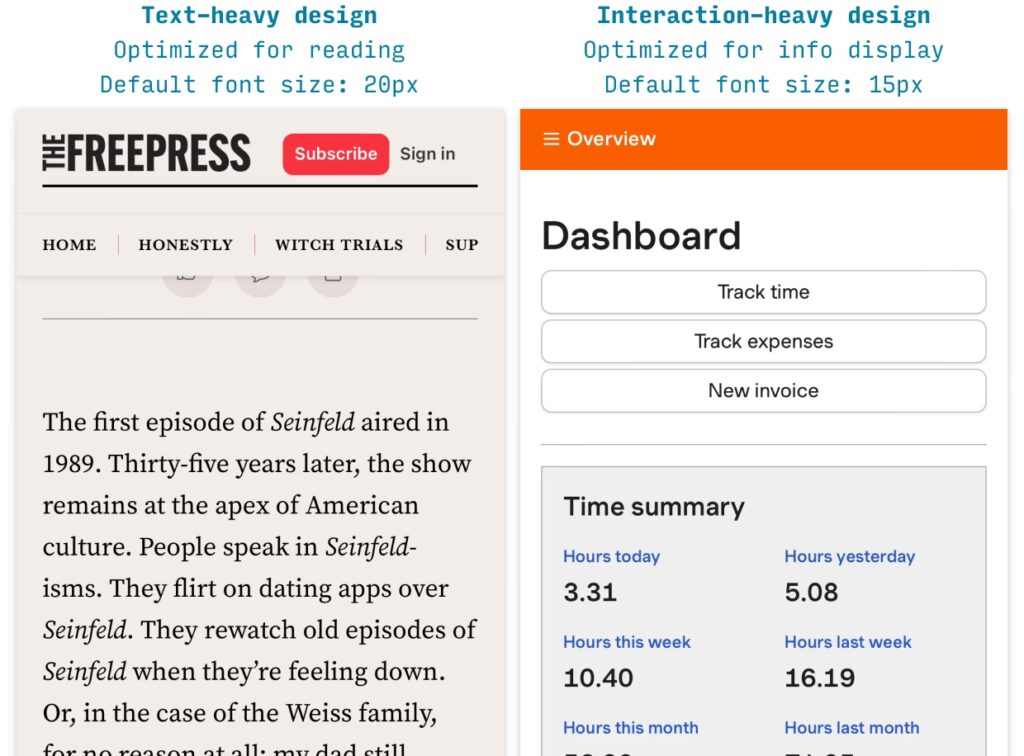
I en verden hvor mobiltelefonen er vores primære adgang til internettet, er det afgørende, at indhold er letlæseligt og behageligt at interagere med. En af de største udfordringer for webdesignere og indholdsskabere er at vælge den rette skriftstørrelse, der sikrer optimal læsbarhed på små skærme uden at kræve konstant zoomning. Dårlig typografi kan hurtigt frustrere brugere og få dem til at forlade din side. Denne omfattende guide vil dykke ned i de bedste praksisser og anbefalinger for at vælge den ideelle skriftstørrelse til mobile skærme, så du kan skabe en gnidningsfri og tilgængelig brugeroplevelse for alle.
Grundlæggende Principper for Mobil Typografi
Mobil typografi handler om struktur, afstand og klarhed for at gøre indholdet let at læse, uanset skærmstørrelsen. Ved at fokusere på nøgleprincipper kan du skabe en brugervenlig oplevelse for alle.
Anbefalede Skriftstørrelser
En af de mest fundamentale anbefalinger er at starte med en grundlæggende skriftstørrelse på 16 pixel for brødtekst. Denne størrelse er bredt anerkendt som den mest komfortable for de fleste læsere og eliminerer behovet for at zoome ind for at læse indholdet. Ud over brødteksten er det essentielt at etablere et klart visuelt hierarki for at guide brugeren gennem indholdet og fremhæve de vigtigste elementer. Dette opnås ved at tildele forskellige skriftstørrelser til forskellige elementer som titler, sekundær tekst og inputfelter.
Anbefalede Skriftstørrelser til Mobilskærme
| Tekstelement | Anbefalet Størrelse (px) |
|---|---|
| Sidetitler / Overskrifter | 28-40px |
| Brødtekst | 16-20px |
| Sekundær Tekst (f.eks. billedtekster, noter) | 14-18px |
| Inputfelter | Mindst 16px |
| Listeemner | 16px (standard) / 14px (tættere lister) |
Linjehøjde og Kontrast
Ud over selve skriftstørrelsen spiller linjehøjden en kritisk rolle for læsbarheden. En god tommelfingerregel er at sætte linjehøjden til 1.5 gange skriftstørrelsen. Dette skaber tilstrækkelig plads mellem tekstlinjerne, hvilket reducerer øjenbelastning og gør det lettere at scanne teksten hurtigt. For eksempel, hvis din brødtekst er 16px, bør linjehøjden være omkring 24px (16 * 1.5). En anden afgørende faktor er kontrasten mellem tekst og baggrund. Ifølge WCAG (Web Content Accessibility Guidelines) anbefales et kontrastforhold på mindst 4.5:1 for normal tekst og 3:1 for stor tekst. Høj kontrast, som sort tekst på en hvid baggrund, er altid et sikkert valg og sikrer maksimal læsbarhed for alle brugere, herunder dem med synsnedsættelser.
Skalerbare Skrifttyper og Fleksibelt Design
For at sikre, at din typografi tilpasser sig problemfrit på tværs af forskellige enhedsstørrelser – fra de mindste smartphones til tablets og desktops – er det essentielt at anvende skalerbare skriftstørrelser. Dette betyder, at man bevæger sig væk fra faste pixelværdier og i stedet benytter sig af relative enheder. Relative enheder tillader teksten at skalere automatisk baseret på skærmstørrelsen, hvilket skaber en mere robust og fremtidssikret typografisk løsning.
Relative Enheder: Em og Rem
De mest almindelige relative enheder er em og rem. En 'em' enhed er relativ til dens forældreelements skriftstørrelse, mens en 'rem' (root em) enhed er relativ til rodfontstørrelsen (typisk defineret på <html> elementet). Dette gør 'rem' særligt nyttig, da en ændring af rodfontstørrelsen automatisk skalerer alle 'rem'-baserede elementer proportionelt. For eksempel, hvis din basefontstørrelse er sat til 16px på <body> eller <html> elementet, vil 1em eller 1rem svare til 16px. En overskrift på 2rem vil så være 32px (2 * 16px). At bruge disse enheder gør det nemt at implementere en responsiv typografi, der justerer sig dynamisk. Ved at sætte breakpoints kan du finjustere skriftstørrelserne for specifikke skærmbredder, hvilket giver dig fuld kontrol over brugeroplevelsen på tværs af enheder.
Test på Rigtige Enheder
Uanset hvor omhyggelig din planlægning og kodning er, er den ultimative test altid at se dine designs på rigtige enheder. En skriftstørrelse, der ser perfekt ud på din store designskærm, kan opføre sig uventet på en lille mobilskærm. Brug værktøjer, der giver dig mulighed for at se dine designs direkte på en mobiltelefon eller tablet. Det er også afgørende at teste, hvordan din tekst skalerer ved at zoome ind til op til 200%. Dette sikrer, at teksten forbliver læselig og at layoutet ikke bryder sammen, hvilket er et vigtigt aspekt af tilgængelighed for brugere med synshandicap.
Detaljerede Retningslinjer for Forskellige Elementer
For at opnå et klart og effektivt design er det vigtigt at forstå, hvordan forskellige tekstelementer skal behandles typografisk på mobile skærme.
Titler og Hovedtekst
Titler er dine brugeres første møde med indholdet, og de skal være iøjnefaldende. Størrelser mellem 28-40px er ideelle til sidetitler, da de skaber et stærkt visuelt anker og guider brugeren. Brødtekst, som udgør størstedelen af dit indhold, bør som nævnt holdes mellem 16-20px for optimal læsekomfort. Det handler om at finde en balance, hvor teksten hverken er for lille til at anstrenge øjnene eller for stor til at virke klodset.
Sekundær Tekst og Inputfelter
Sekundær tekst, såsom billedtekster, undertekster eller mindre vigtige detaljer, kan være lidt mindre end brødteksten, typisk 14-18px. Det er vigtigt, at der stadig er en tydelig forskel i størrelse, så det ikke forveksles med den primære tekst. En generel anbefaling er at gøre sekundær tekst omkring 2 størrelser mindre end din brødtekst for at sikre en klar visuel adskillelse. For inputfelter er det en streng regel: skriftstørrelsen skal være mindst 16px. Hvis den er mindre, vil iOS-browsere automatisk zoome ind på feltet, hvilket ofte skjuler dele af formularen og tvinger brugeren til manuelt at zoome ud, hvilket er en dårlig brugeroplevelse.
Lister og Specifikke OS-standarder
Lister er et almindeligt element på mobile sider. Standardlisteelementer er ofte 16px, men tættere lister, som dem i sidepaneler, kan være 14px, eventuelt med en federe vægt for at kompensere. Det er også værd at bemærke, at forskellige operativsystemer (OS) har deres egne typografiske retningslinjer, som det kan være nyttigt at kende til, især hvis du designer apps. Androids Material Design anbefaler for eksempel 16sp (scalable pixels) for standard brødtekst og listeelementer, og 20sp for titler. iOS's retningslinjer for SF Pro-skrifttypen angiver 17px som standard for brødtekst og 15px for sekundær tekst. Selvom disse er specifikke for apps, giver de en god indikation af, hvad brugerne forventer af læsbarhed på mobile enheder.
Optimering for Læsevenlighed og Tilgængelighed
God typografi går hånd i hånd med tilgængelighed. Her er yderligere tips til at forbedre læsevenligheden for alle brugere.
Tegn pr. Linje og Skrifttypevalg
For at optimere læsevenligheden yderligere, bør du sigte efter 30-40 tegn pr. linje på mobile skærme. Dette minimerer øjenbevægelser og gør teksten lettere at følge. Når det kommer til valg af skrifttype, er sans-serif skrifttyper som Arial, Open Sans eller Roboto generelt at foretrække på digitale skærme, især små mobilskærme. Deres rene linjer og fravær af dekorative udsmykninger (serif'er) gør dem mere læselige ved mindre størrelser. Selvom seriffonter kan bruges, bør de testes grundigt for læsbarhed på mobil, især i mørk tilstand.
WCAG Retningslinjer for Kontrast
At overholde WCAG's retningslinjer for kontrast er ikke kun et spørgsmål om design, men også om tilgængelighed. En høj kontrast sikrer, at dit indhold er læseligt for alle, uanset synsevne. Et klassisk eksempel er sort tekst (#000000) på en hvid baggrund (#FFFFFF), som giver et fremragende kontrastforhold.
Anbefalede Kontrastforhold (WCAG)
| Element | Anbefalet Kontrastforhold |
|---|---|
| Normal Tekst | 4.5:1 minimum |
| Stor Tekst (24px+ eller 18px+ fed) | 3:1 minimum |
| Interaktive Elementer (f.eks. ikoner, knapper) | 3:1 minimum |
Det er vigtigt at sikre, at selv interaktive elementer har tilstrækkelig kontrast, så de er tydelige og brugbare for alle.
Fremtidens Typografi: Intrinsic Type
Mens vi i dag fokuserer på responsiv typografi med relative enheder og breakpoints, kigger fremtiden mod 'intrinsic typography'. Dette er et koncept, hvor tekstens stil defineres ud fra dens proportion til det område, den befinder sig i, snarere end viewporten. Målet er at øge fleksibiliteten og forenkle koden. Resultatet er, at tekst 'selvjusterer' sig til sin container, hvilket potentielt kan give en næsten ubegrænset variation af skriftstørrelser, der passer perfekt til ethvert rum. Selvom dette stadig er et område under udvikling, understreger det vigtigheden af at tænke fremadrettet og designe med fleksibilitet for øje.
Konklusion
At vælge den rette skriftstørrelse til mobile skærme er en grundsten i godt webdesign og en afgørende faktor for brugeroplevelsen. Ved at følge de grundlæggende principper – en solid basefontstørrelse på 16px for brødtekst, anvendelse af relative enheder som em eller rem, etablering af et klart visuelt hierarki, sikring af høj kontrast og regelmæssig test på rigtige enheder – kan du skabe en hjemmeside, der ikke kun ser flot ud, men også er yderst læsbar og tilgængelig for alle. Husk, at målet er at gøre læsning på mobil lige så behageligt som at læse en veldesignet bog. Ved at prioritere typografien løfter du din mobilside fra funktionel til fremragende.
Ofte Stillede Spørgsmål (FAQs)
Hvilken skriftstørrelse fungerer bedst til mobilskærme?
For let læsning på mobile enheder anbefales det at bruge en minimum skriftstørrelse på 16px for brødtekst. Denne størrelse gør det muligt for brugere at læse komfortabelt uden at skulle zoome ind eller anstrenge øjnene. Det er en bredt accepteret standard for mobil typografi og sikrer en god grundlæggende læsbarhed for de fleste brugere.
Hvad er de vigtigste typografitips for mobilapps?
Selvom denne guide primært fokuserer på websites, gælder mange af de samme principper for mobilapps. Her er nogle essentielle typografitips:
- Brødtekst: Brug mindst 16px til hovedindholdet.
- Overskrifter: Gør overskrifter omkring 1.3 gange større end brødteksten for at skabe et klart hierarki.
- Linjeafstand: Sæt linjeafstanden til 1.5 gange skriftstørrelsen for forbedret læsbarhed.
- Skrifttype: Vælg sans-serif skrifttyper, da de generelt er nemmere at læse på skærme.
Disse praksisser sikrer, at din app fremstår ren, er nem at navigere i og opfylder forventninger til tilgængelighed.
Hvad er den mindste acceptable skriftstørrelse for en mobilside?
Mens 16px er den foretrukne størrelse for brødtekst, er der visse undtagelser for mindre vigtig tekst:
- Hovedindhold: Hold dig til 16px eller større.
- Billedtekster eller Fodnoter: 14px kan fungere for mindre kritisk tekst.
- Juridisk Tekst: 14px er også acceptabelt for juridiske ansvarsfraskrivelser, især hvis de er skrevet med store bogstaver eller med bredere afstand.
Generelt er tommelfingerreglen, at skriftstørrelsen skal være 16px for mobile websites. Alt mindre end det kan kompromittere læsbarheden for synshandicappede læsere og forringe den generelle brugeroplevelse.